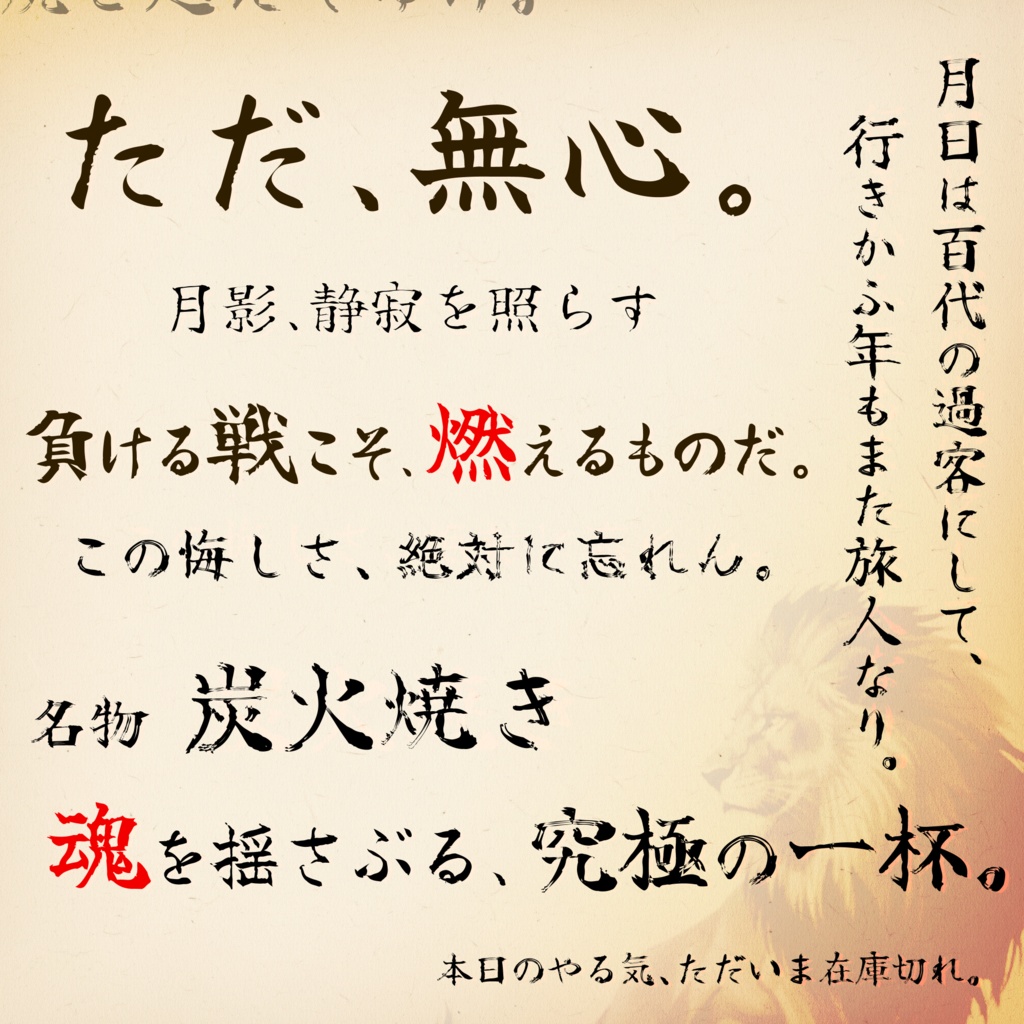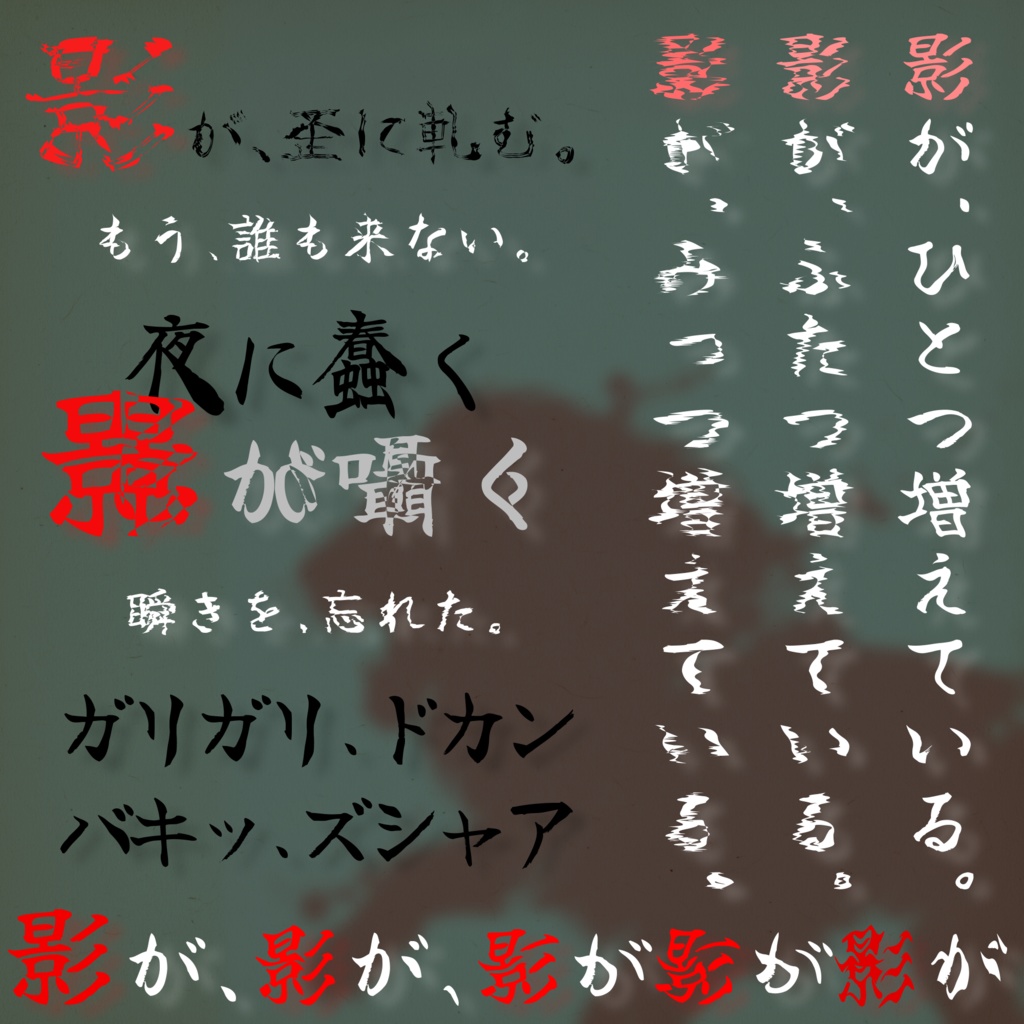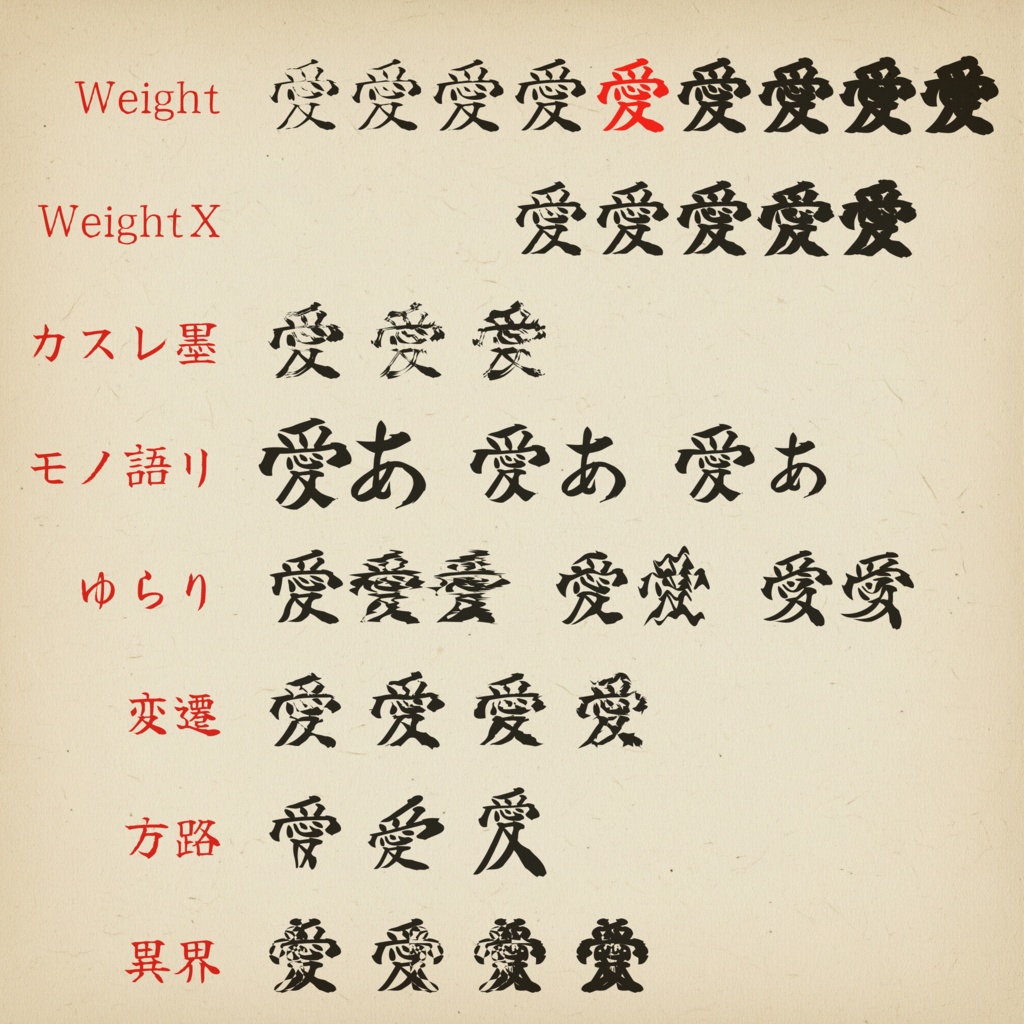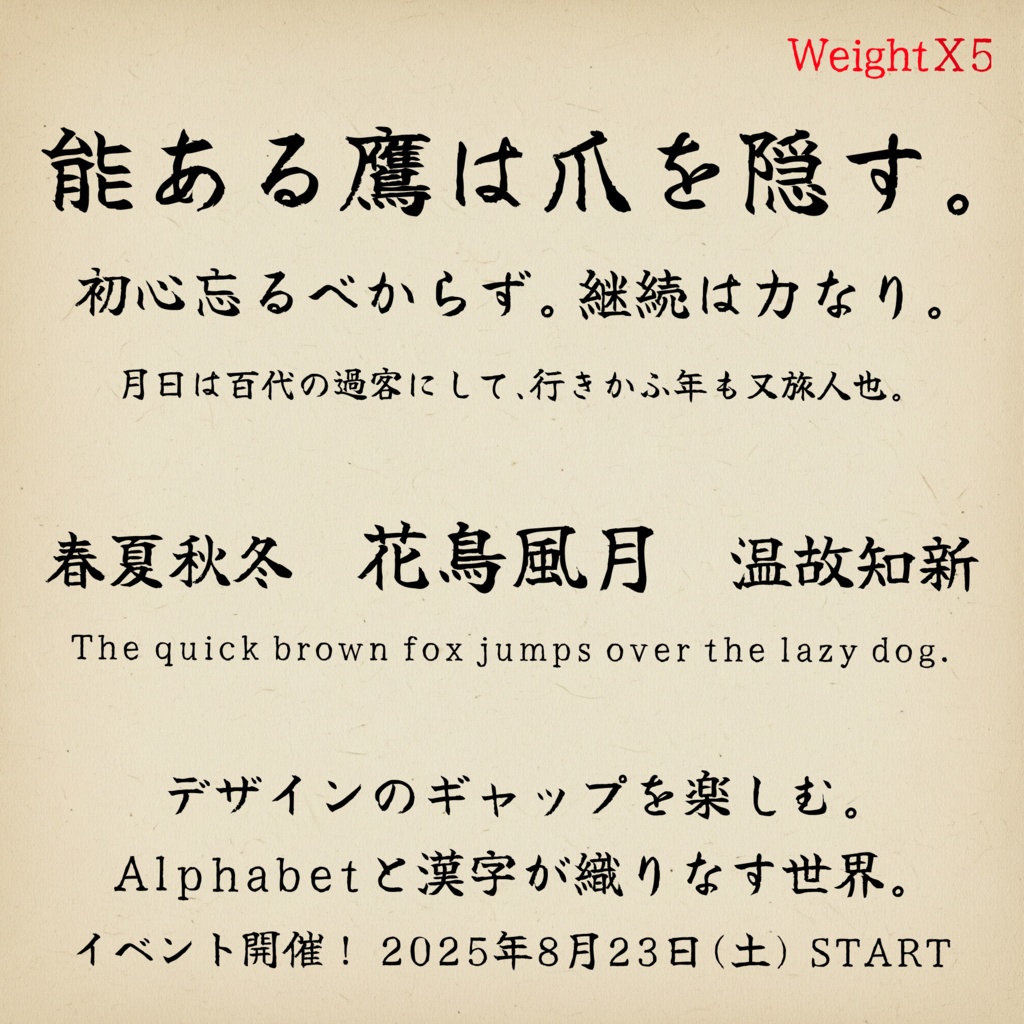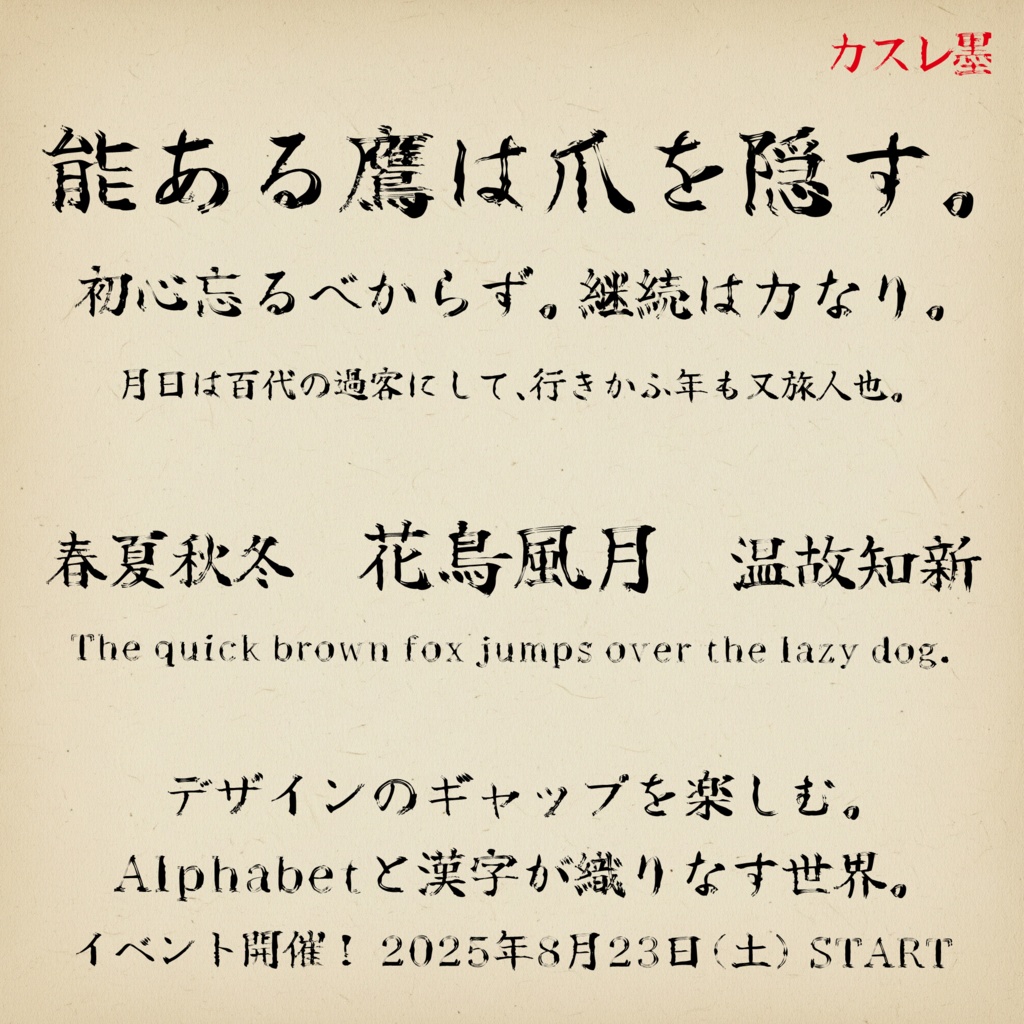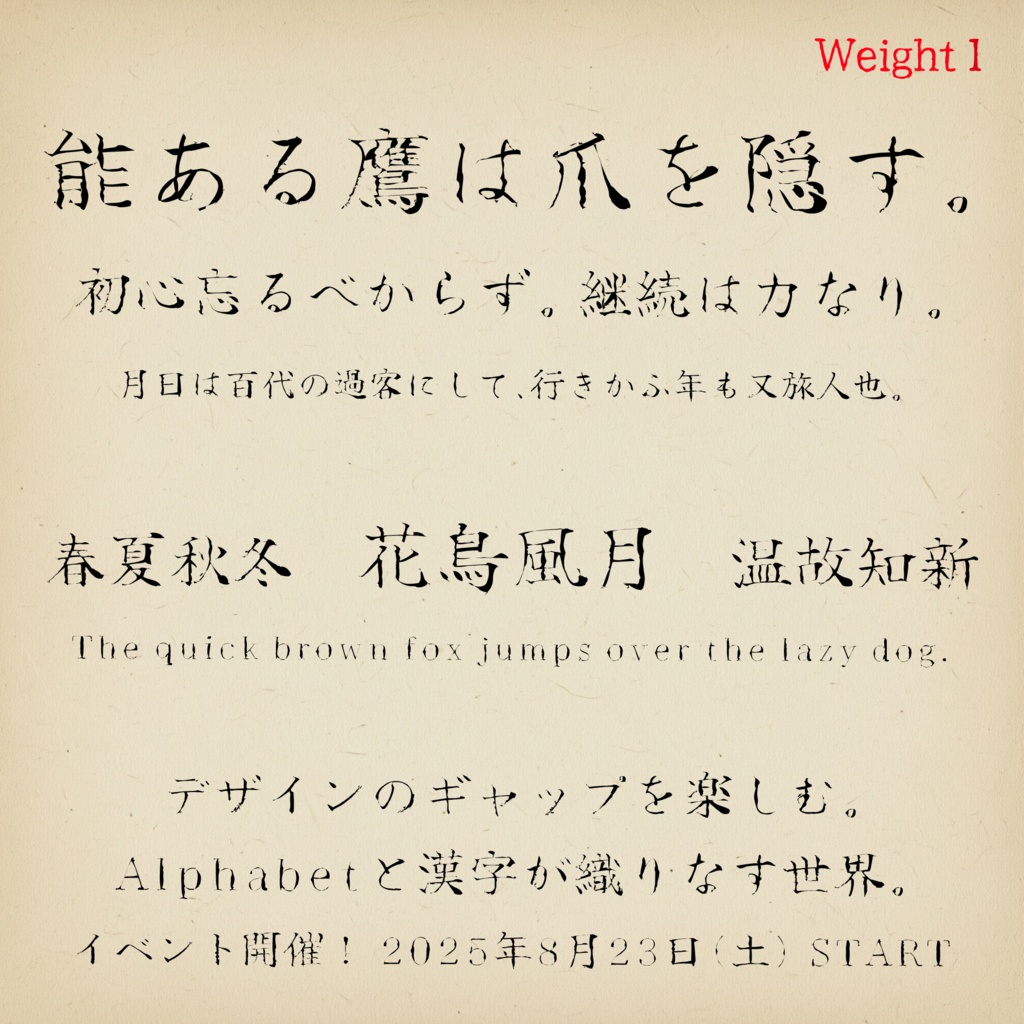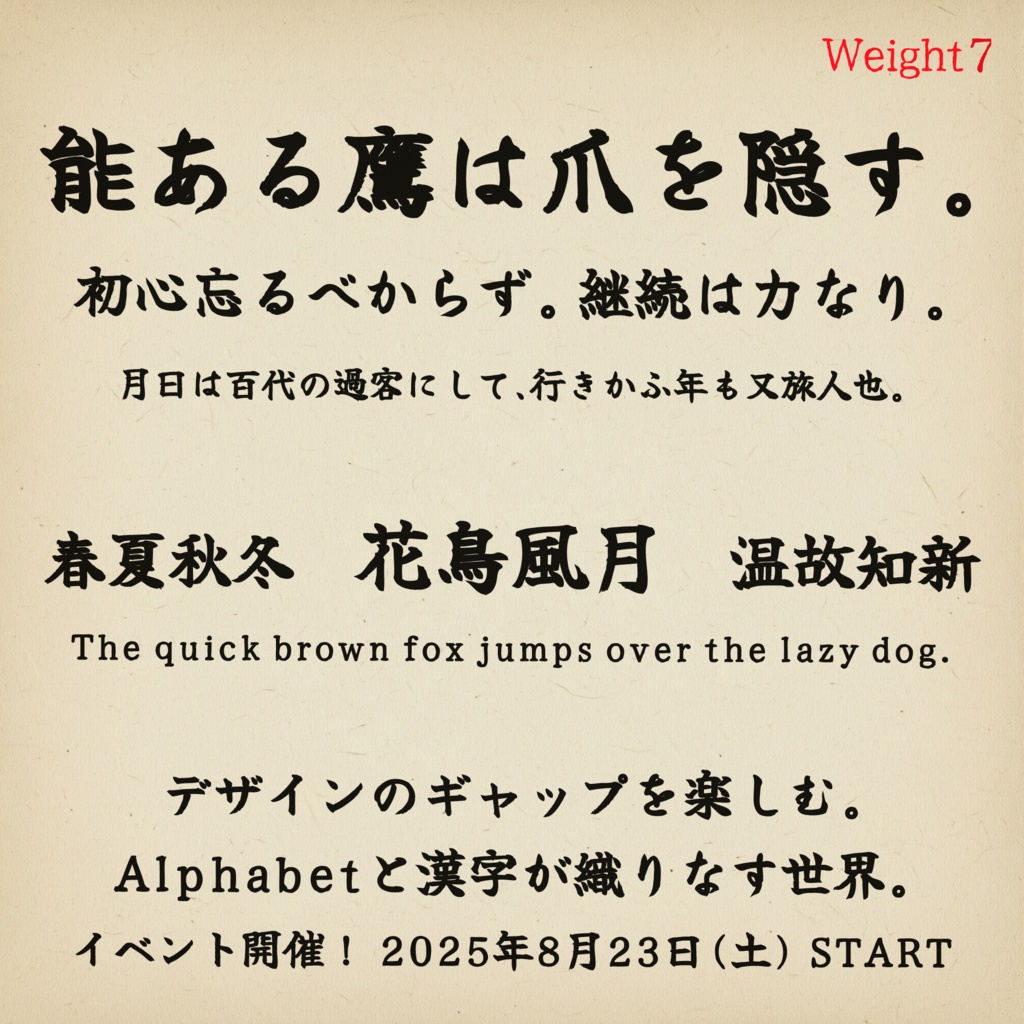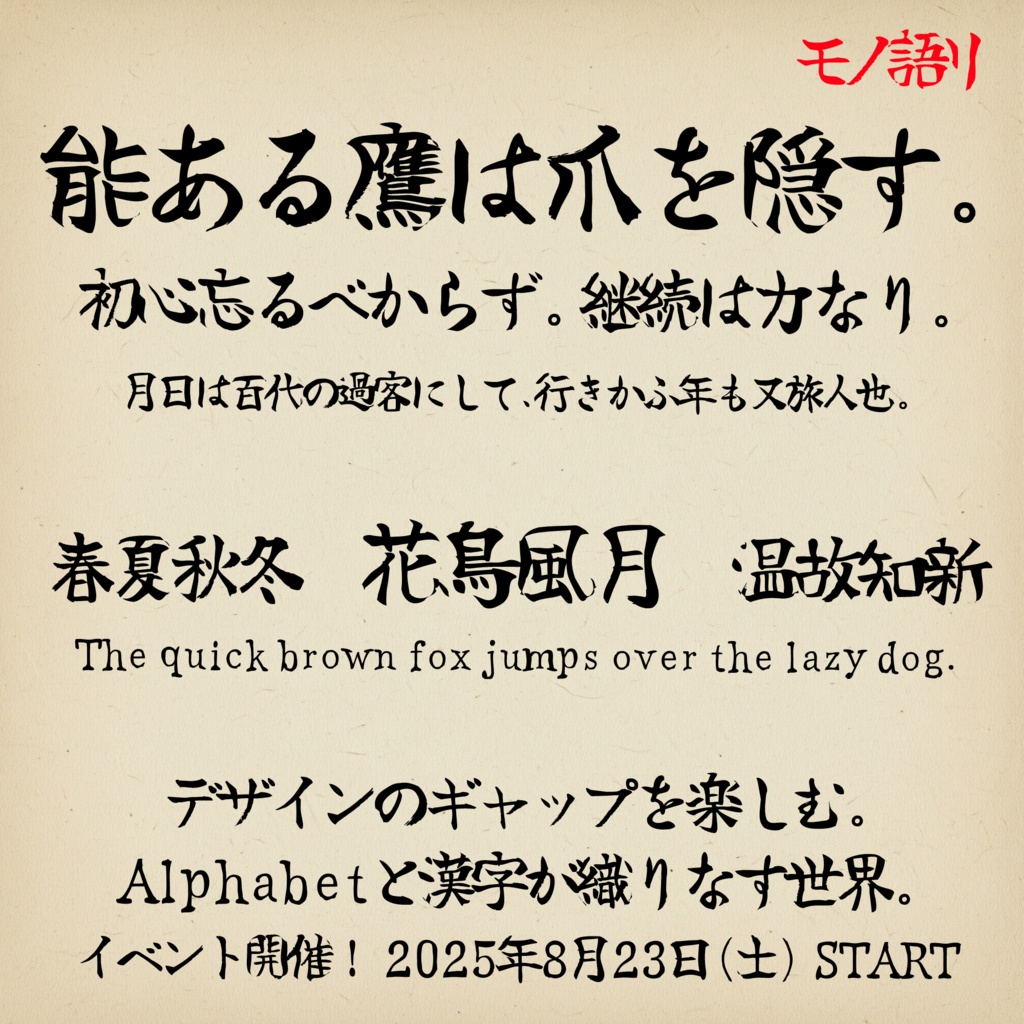
筆文字書体『勇獅子』【フリーフォント】
『勇獅子』(YuJishi) 力強い文字表現や、怪しさの演出等に。 多彩なバリエーションが特徴の筆文字フォントです。 本フォントは、オープンソースフォント 『佑字【肅】』(YujiSyuku-Regular) https://github.com/Kinutafontfactory/Yuji を元に制作しました。 素晴らしいフォントを公開してくださった制作者様に心より感謝申し上げます。
多くの書体を同梱。 おすすめは「各 Weight」「カスレ墨1」「モノ語リ」「変遷」です。 ■ Weight(1~9) 基本となる 太字化 / 細字化 フォントです。 「Weight 5」が元フォントと同一の太さとなります。 ■ Weight X(4~8) よりアナログ風味なゆらぎを加えた 太字化 / 細字化 フォントです。 ■ カスレ墨(1~3) かすれた筆文字風のフォントです。 ■ モノ語リ(1~3) 球状のユニークな歪みが特徴のフォントです。 漢字部分を置き換える「混植」利用もおすすめです。 ■ ゆらり(1~3) 水面の波紋のように、ゆらりと揺らめく字形のフォントです。 ■ 変遷(1~4) 風化したような表現など、独特なニュアンスを加えたフォントです。 ■ 方路(1~3) 特定の方向に引き伸ばされたような形状のフォントです。 ■ 異界(1~4) 反転字形の重ね合わせによる、デザイン・演出向けのフォントです。